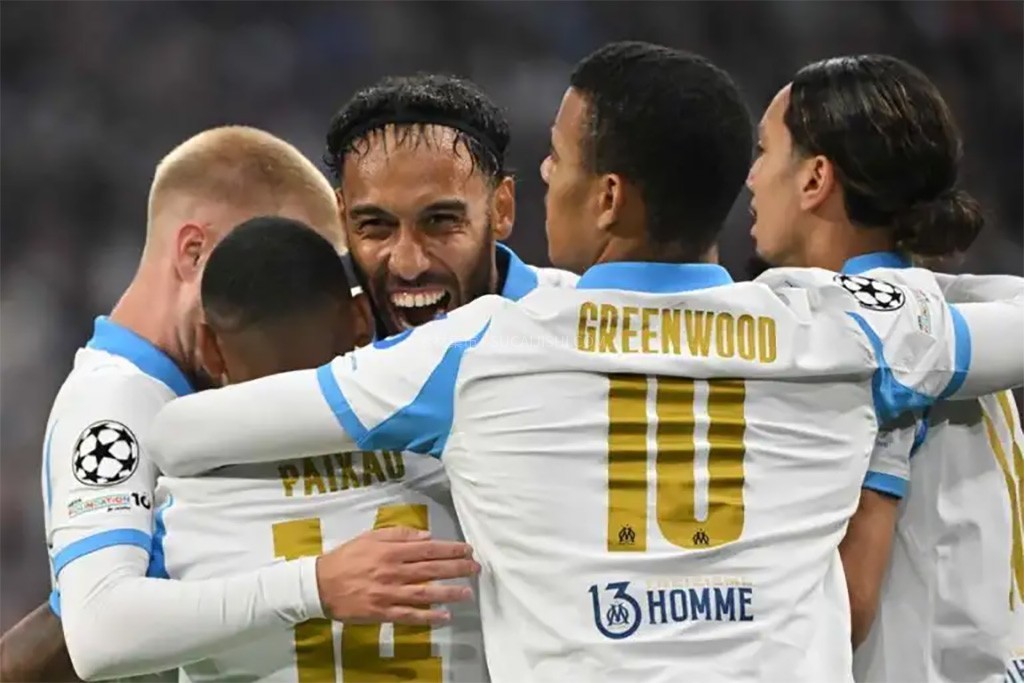
马赛奥林匹克 2025-2026 赛季欧冠字体
这款马赛奥林匹克足球俱乐部 – 2025/2026 赛季欧冠字体,将这家法国俱乐部的标志性风格融入您的设计之中。这款足球字体从马赛在 2025/2026 赛季欧冠联赛中使用的球衣字体中汲取灵感。无论您是设计球衣、海报、球迷周边产品还是数字视觉作品,这款字体都能提升您的设计水平,并将马赛的拼搏精神融入您的作品之中。